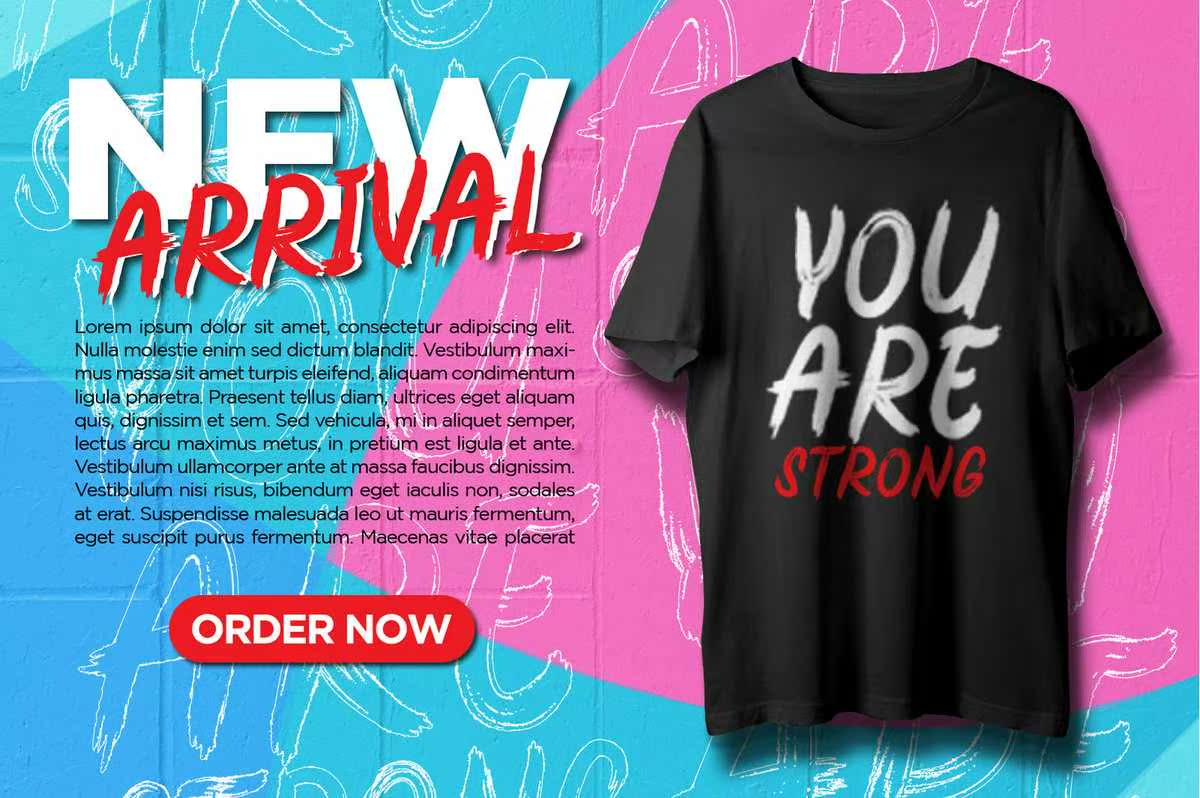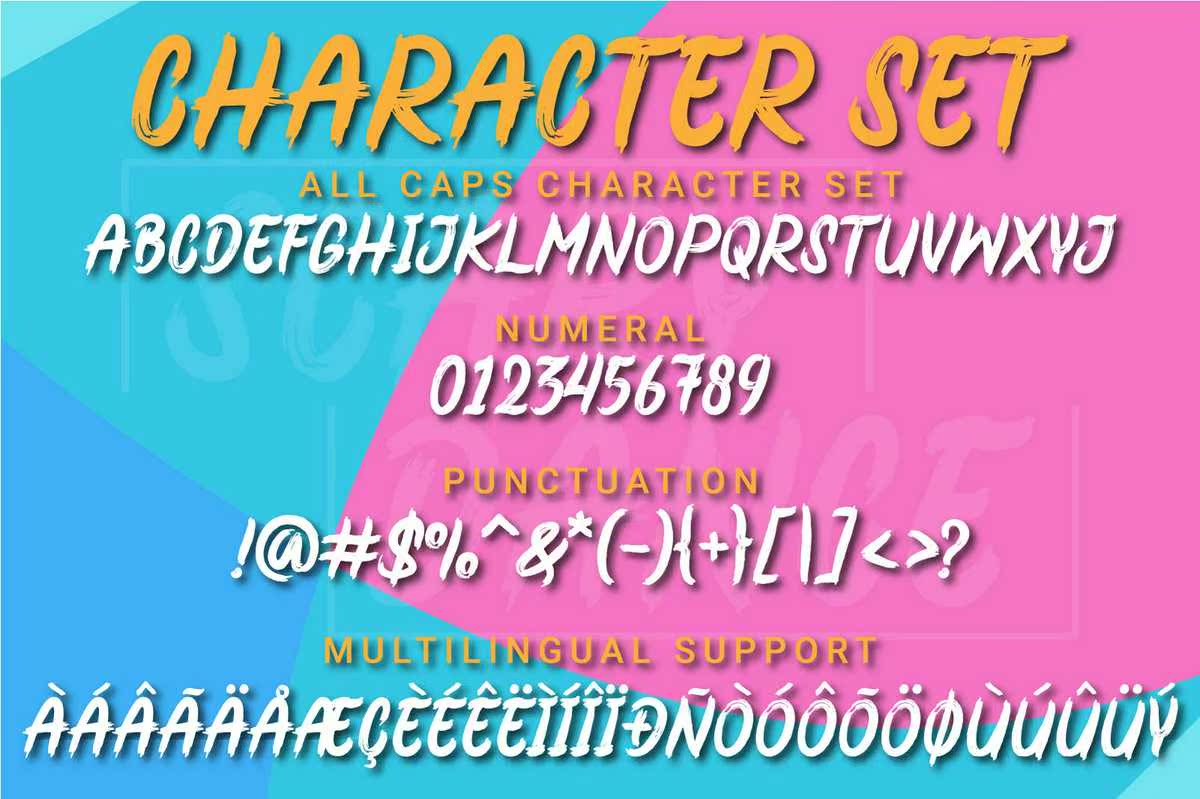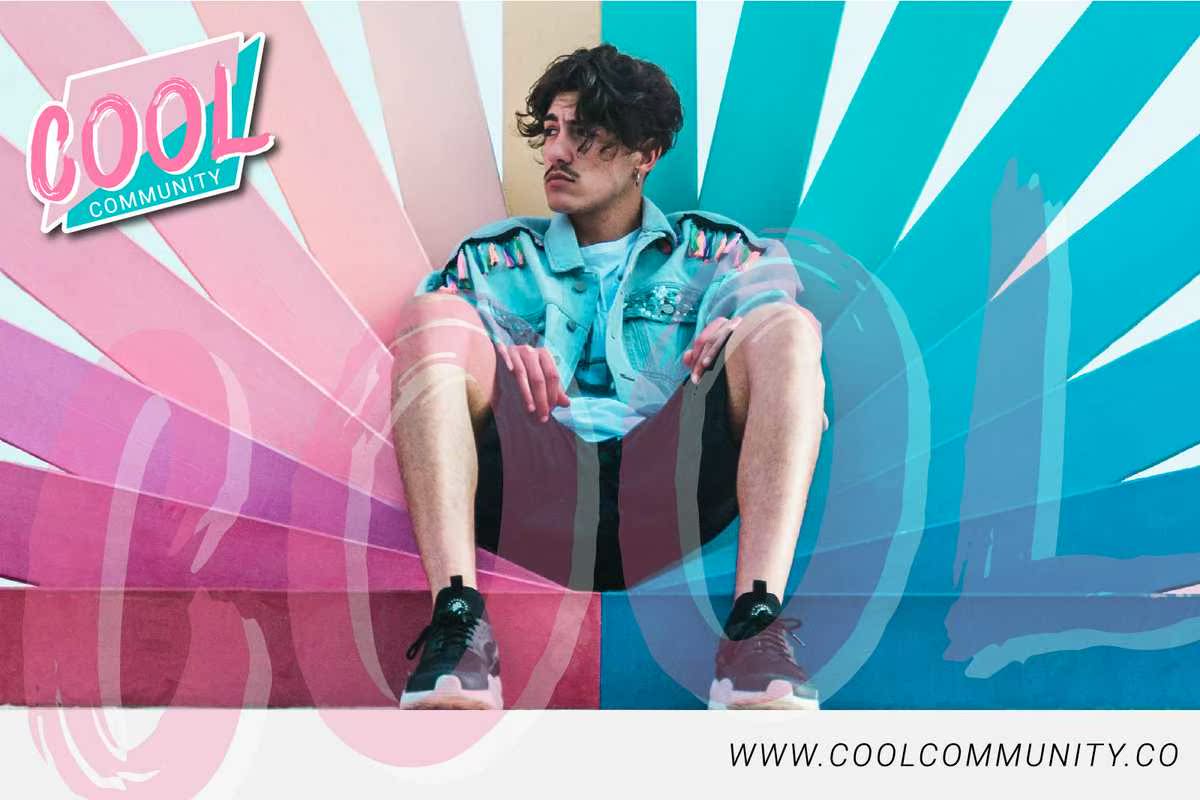
SCARYDANCE是一款酷炫的粗体显示字体。项目主体显示了所有儿童活动或学校项目、海报、包装、广告、新闻标题、品牌、标志以及任何你想要的浪漫城市外观和感觉。此字体将把任何创造性的想法变成一个工作屁!SCARYDANCE是一款酷炫的粗体显示字体。项目主体显示了所有儿童活动或学校项目、海报、包装、广告、新闻标题、品牌、标志以及任何你想要的浪漫城市外观和感觉。此字体将把任何创造性的想法变成一个工作屁!